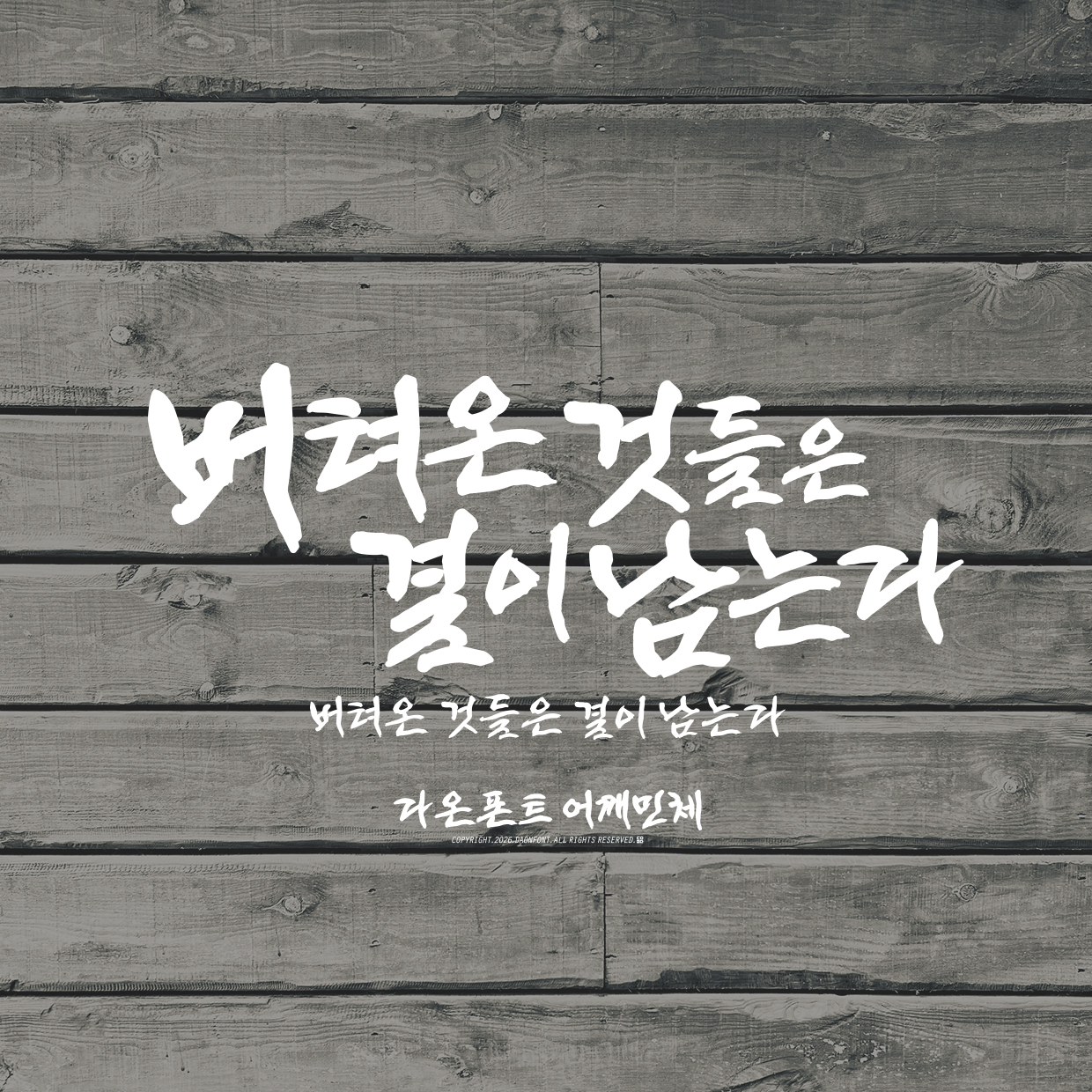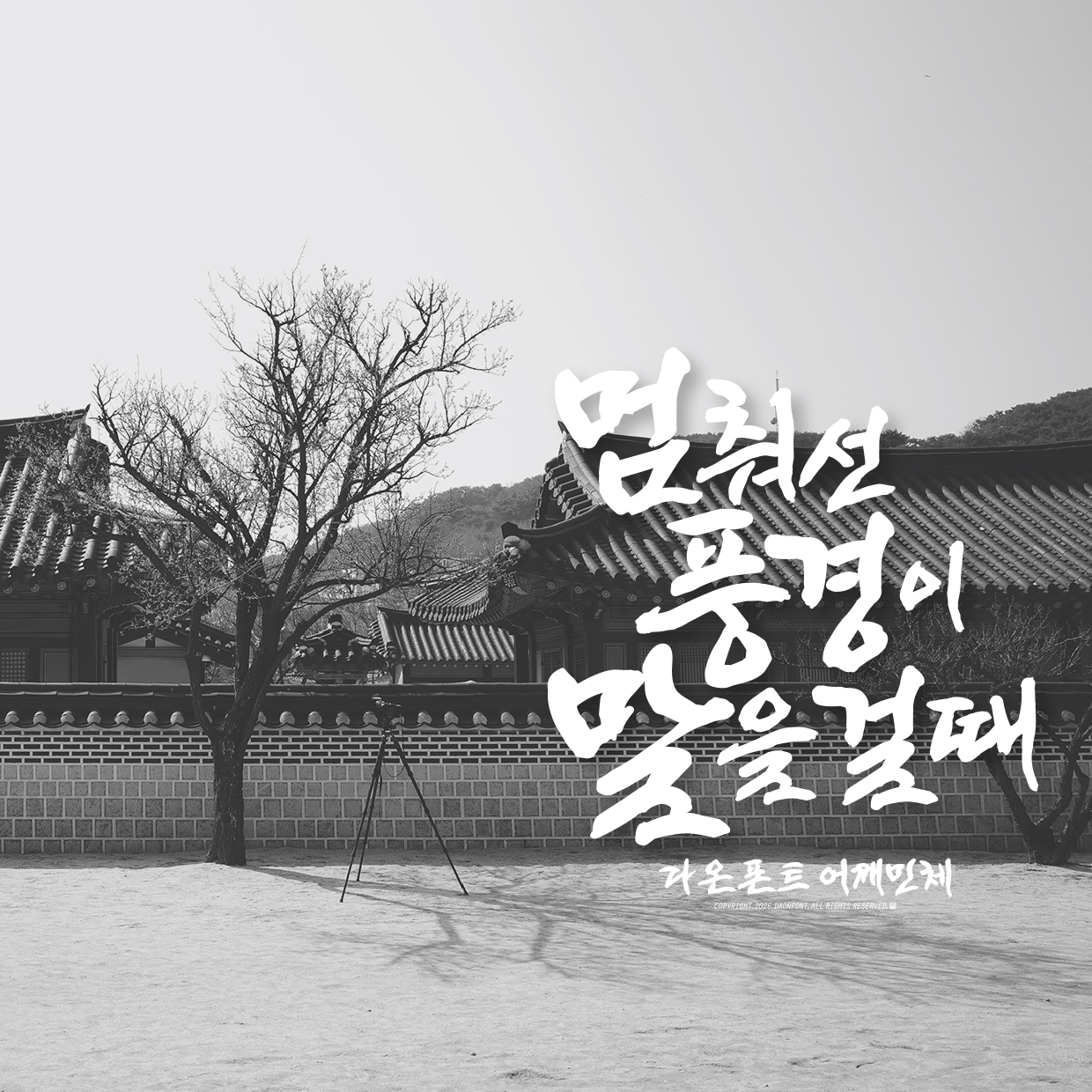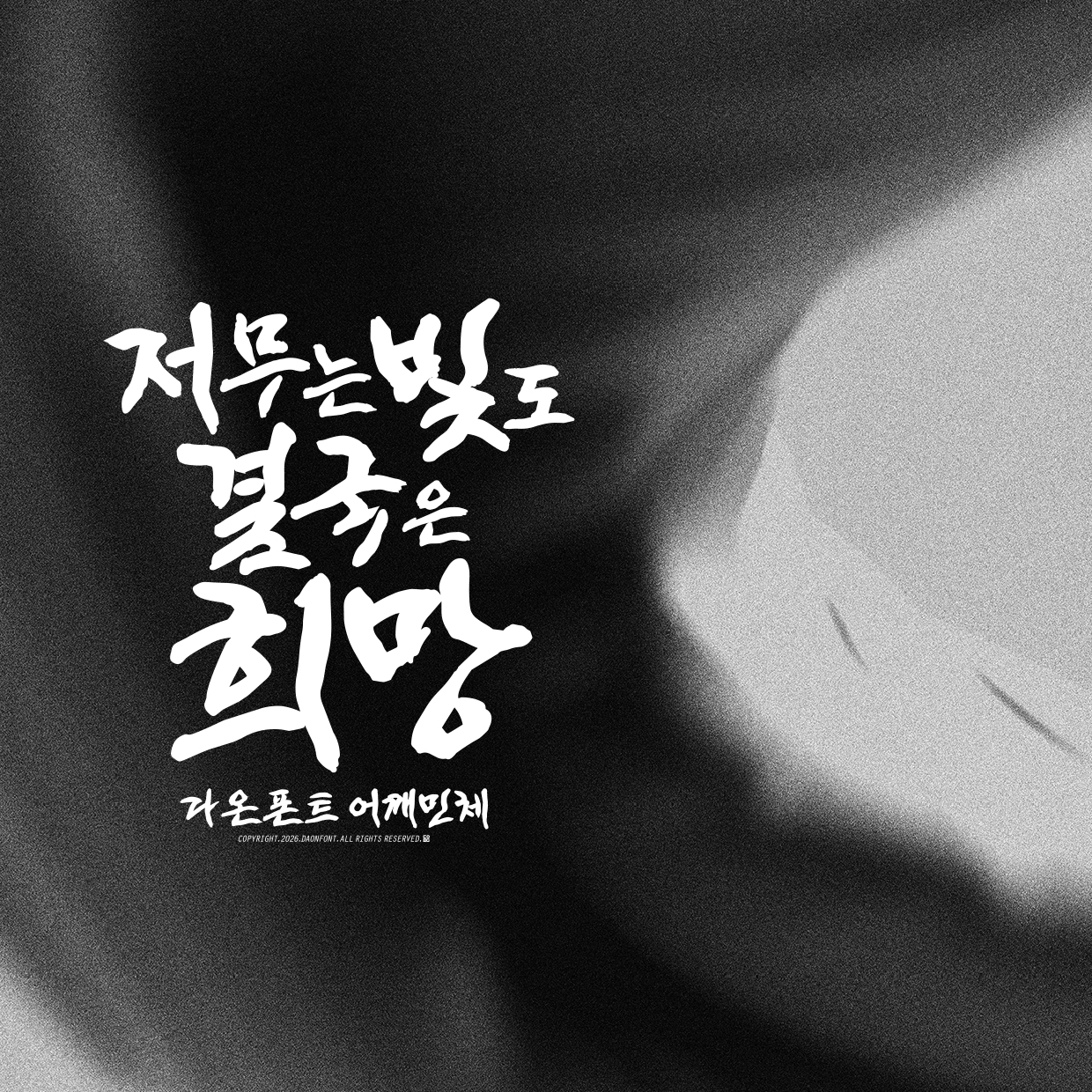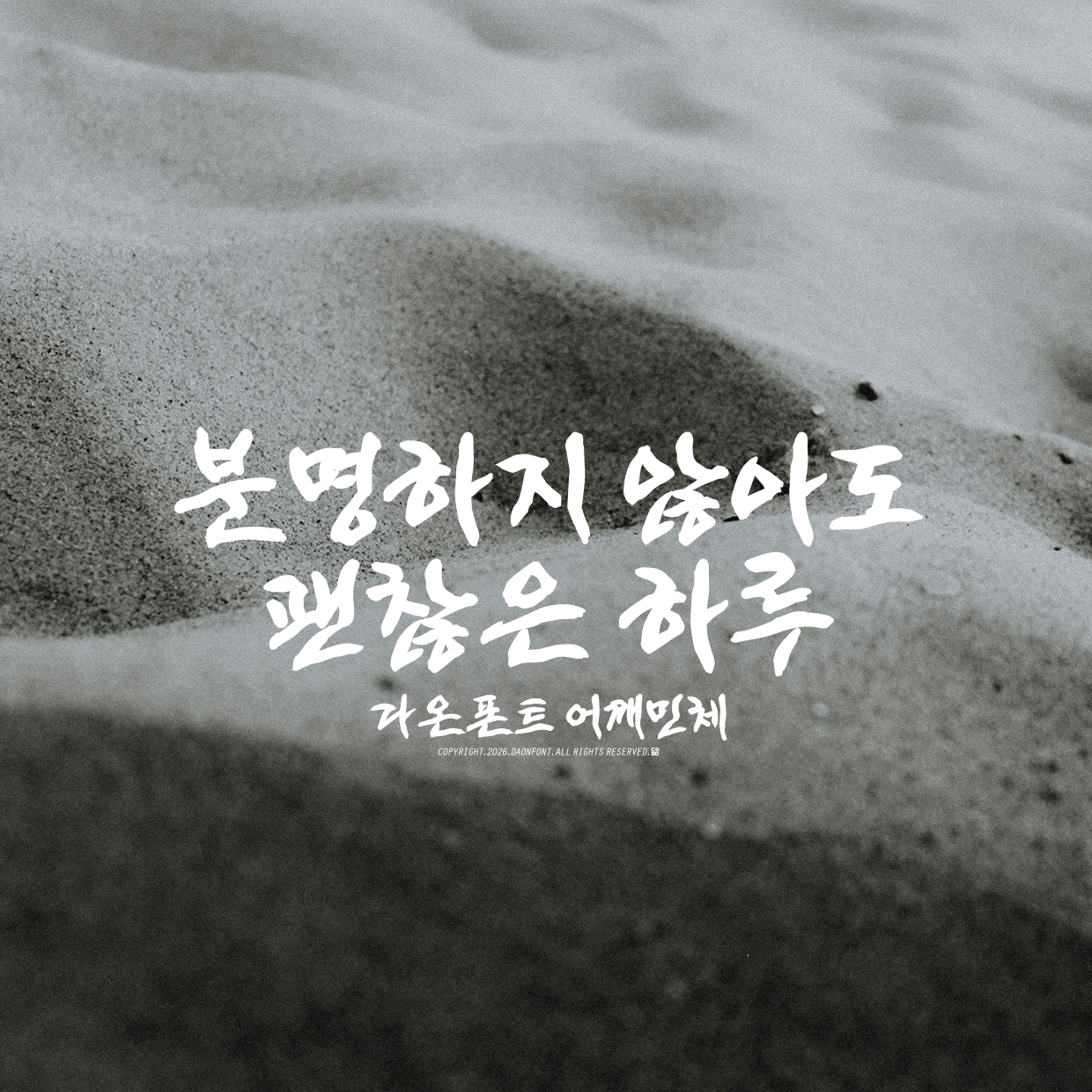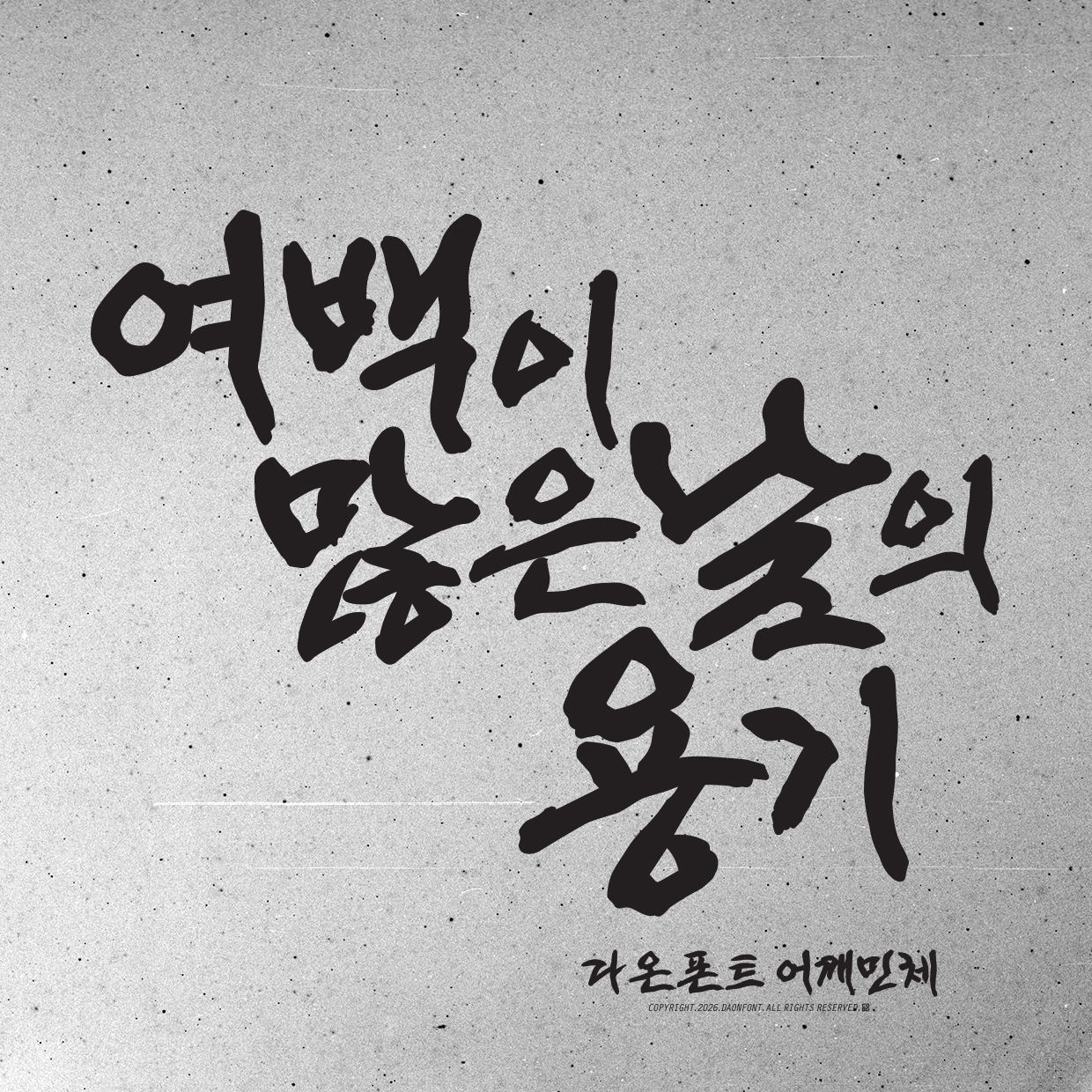
다온폰트 신서체 "어깨민체" 출시
2026년 1월 27일 "다온폰트 어깨민체"가 출시 되었습니다.
어깨민체는 민체의 구조적 안정감을 기반으로 한 캘리그라피 폰트로,
문장 단위에서의 읽힘과 균형을 중점에 두고 설계된 서체입니다.
Regular, Medium, Bold 3종 웨이트로 구성되어 있으며,
출판, 기록, 브랜딩 등 다양한 텍스트 환경에서 안정적으로 사용할 수 있습니다.